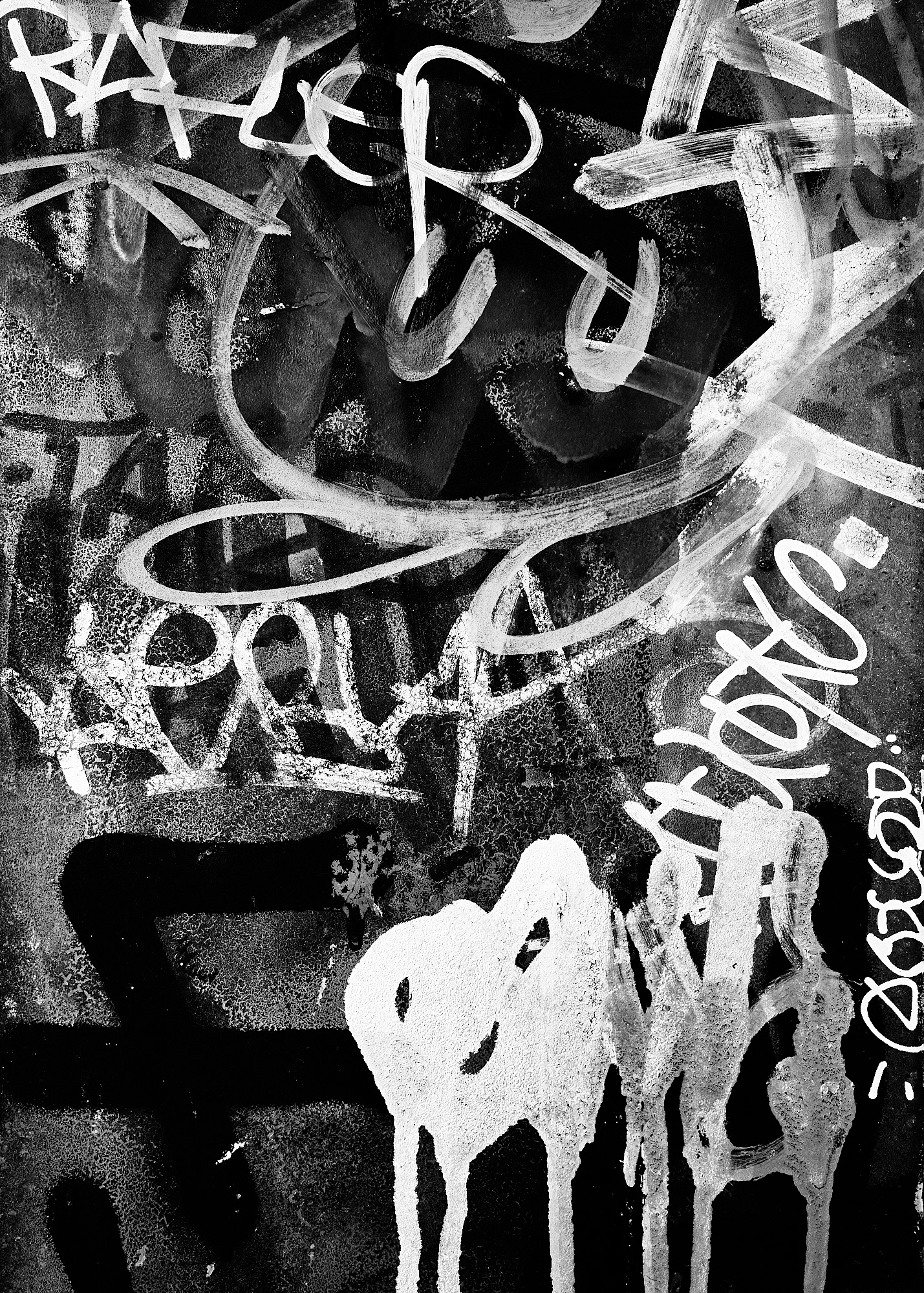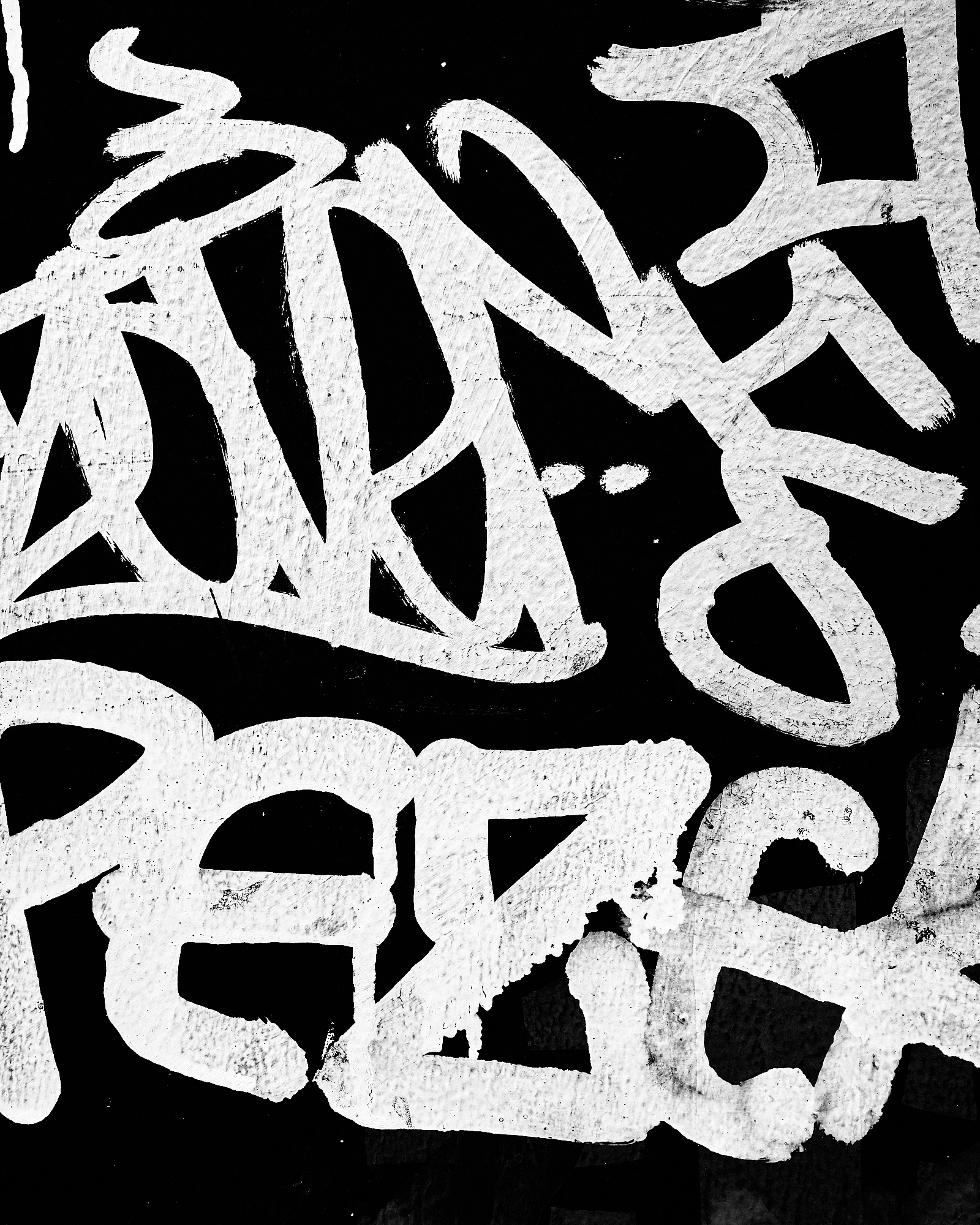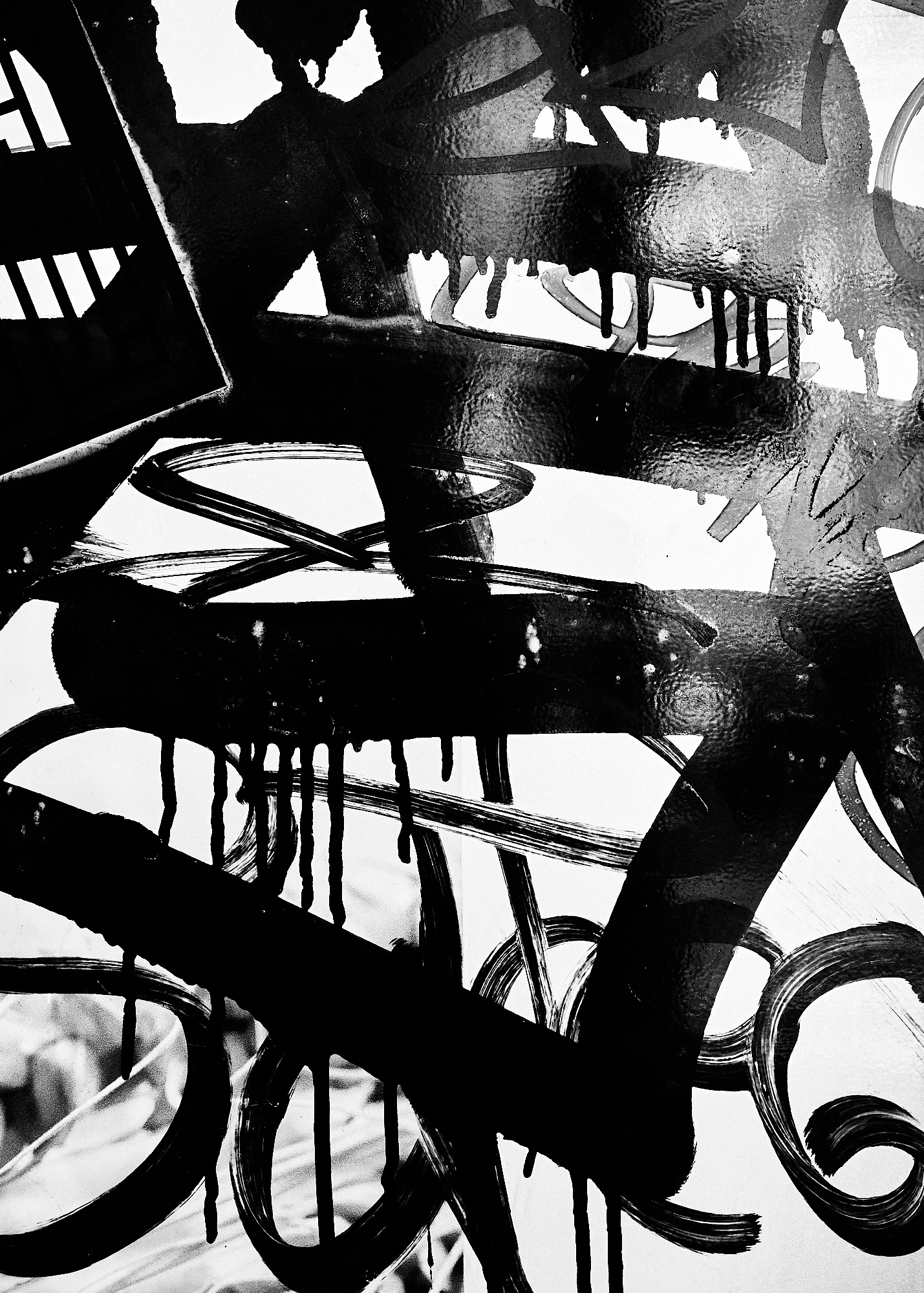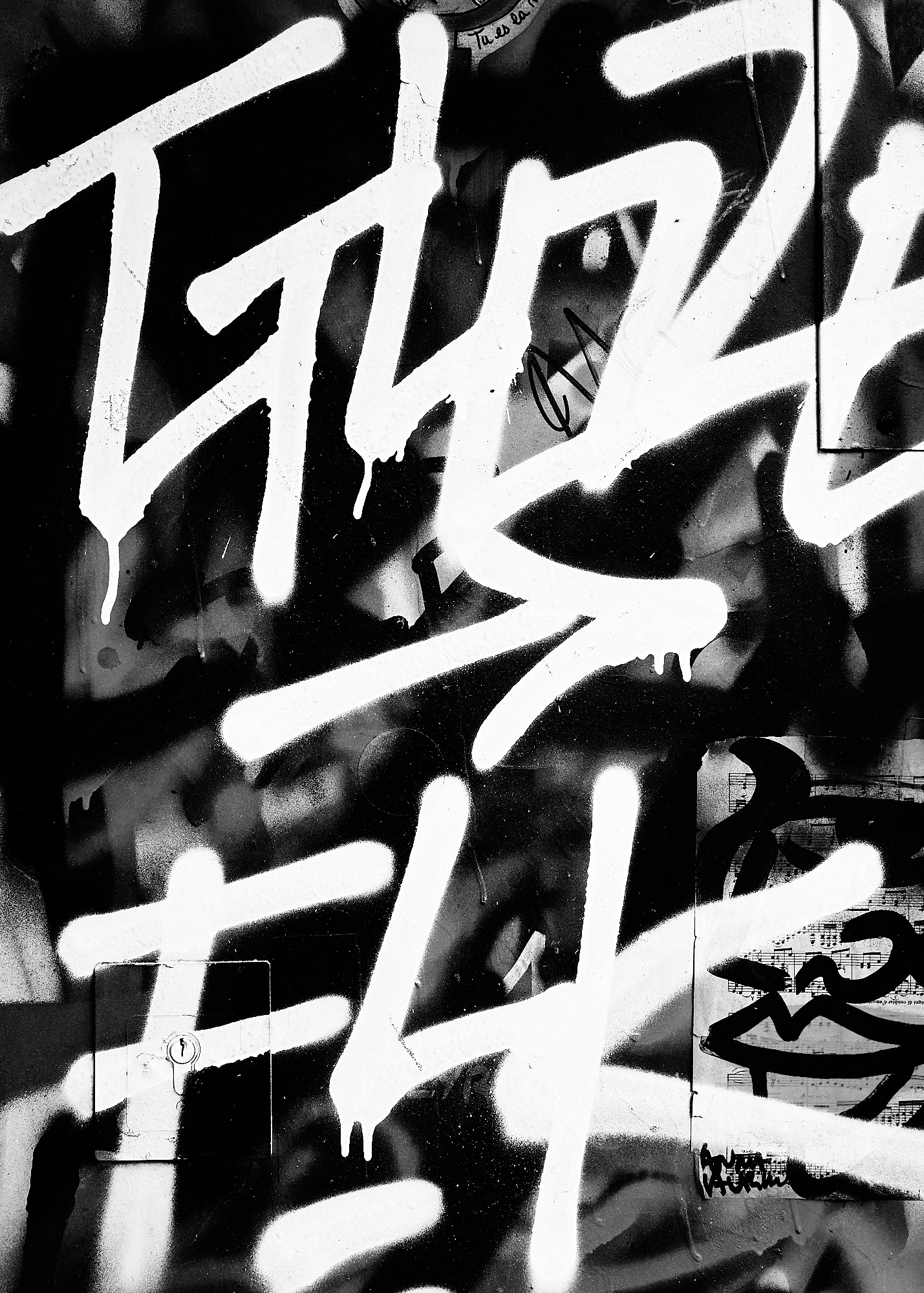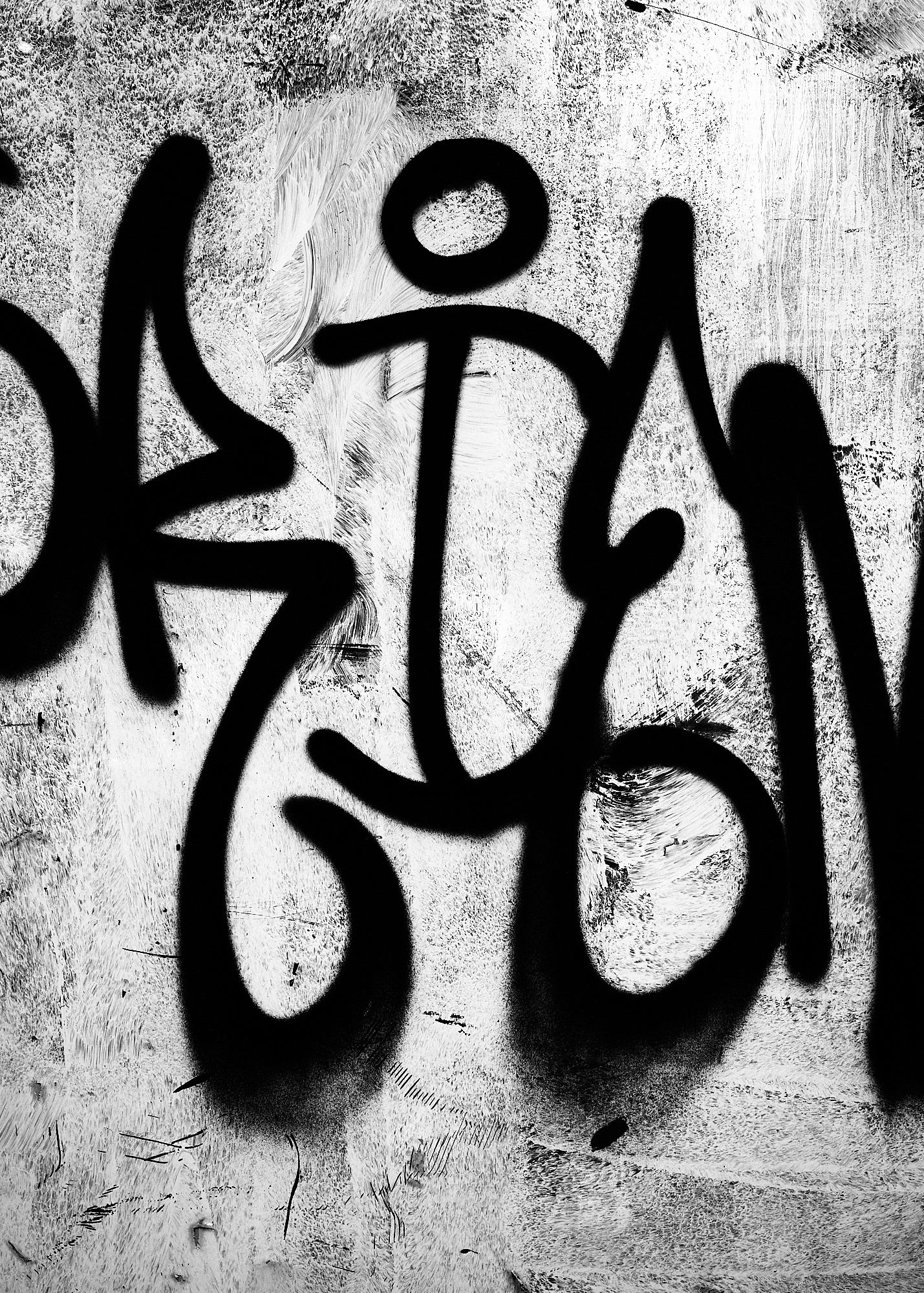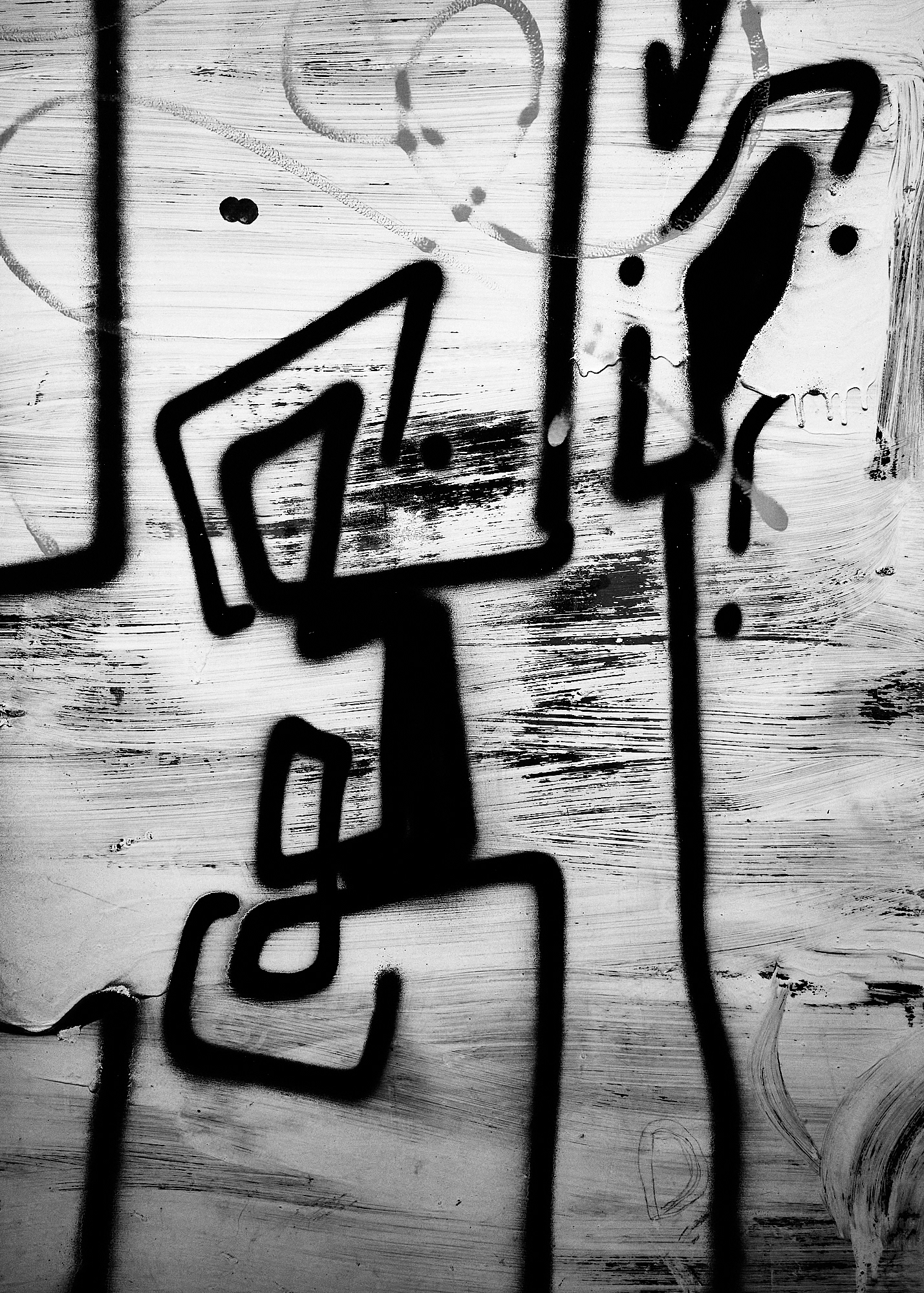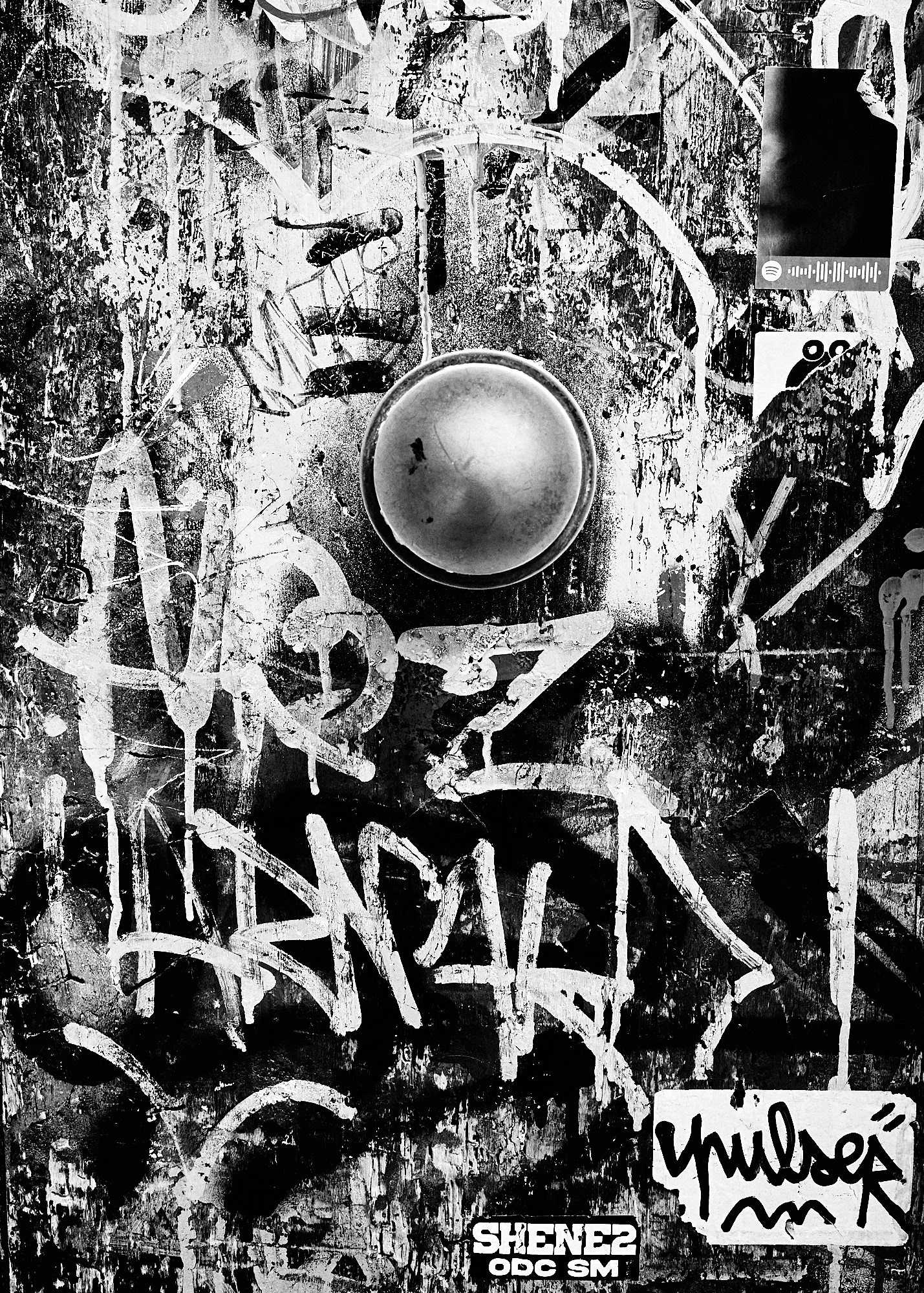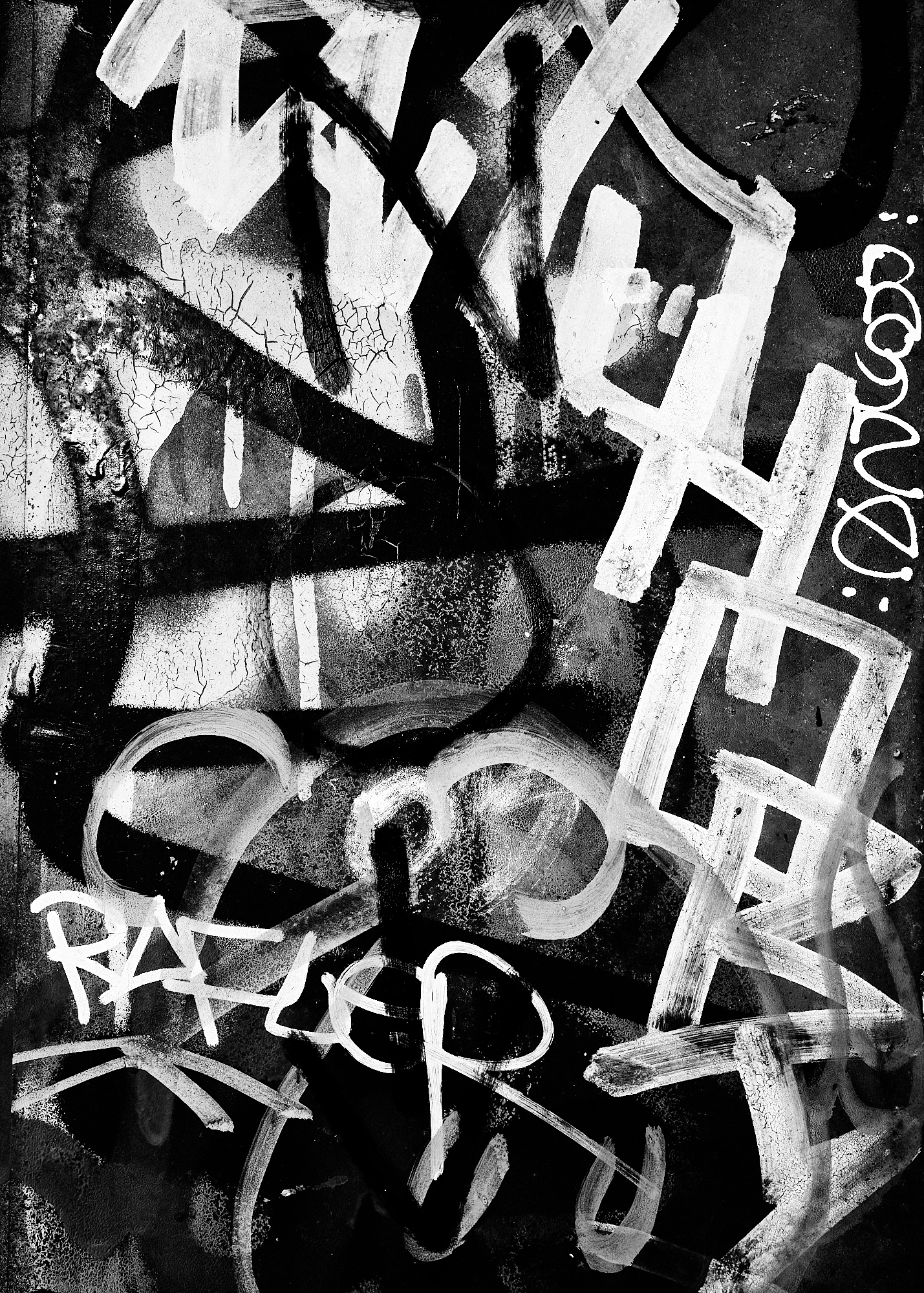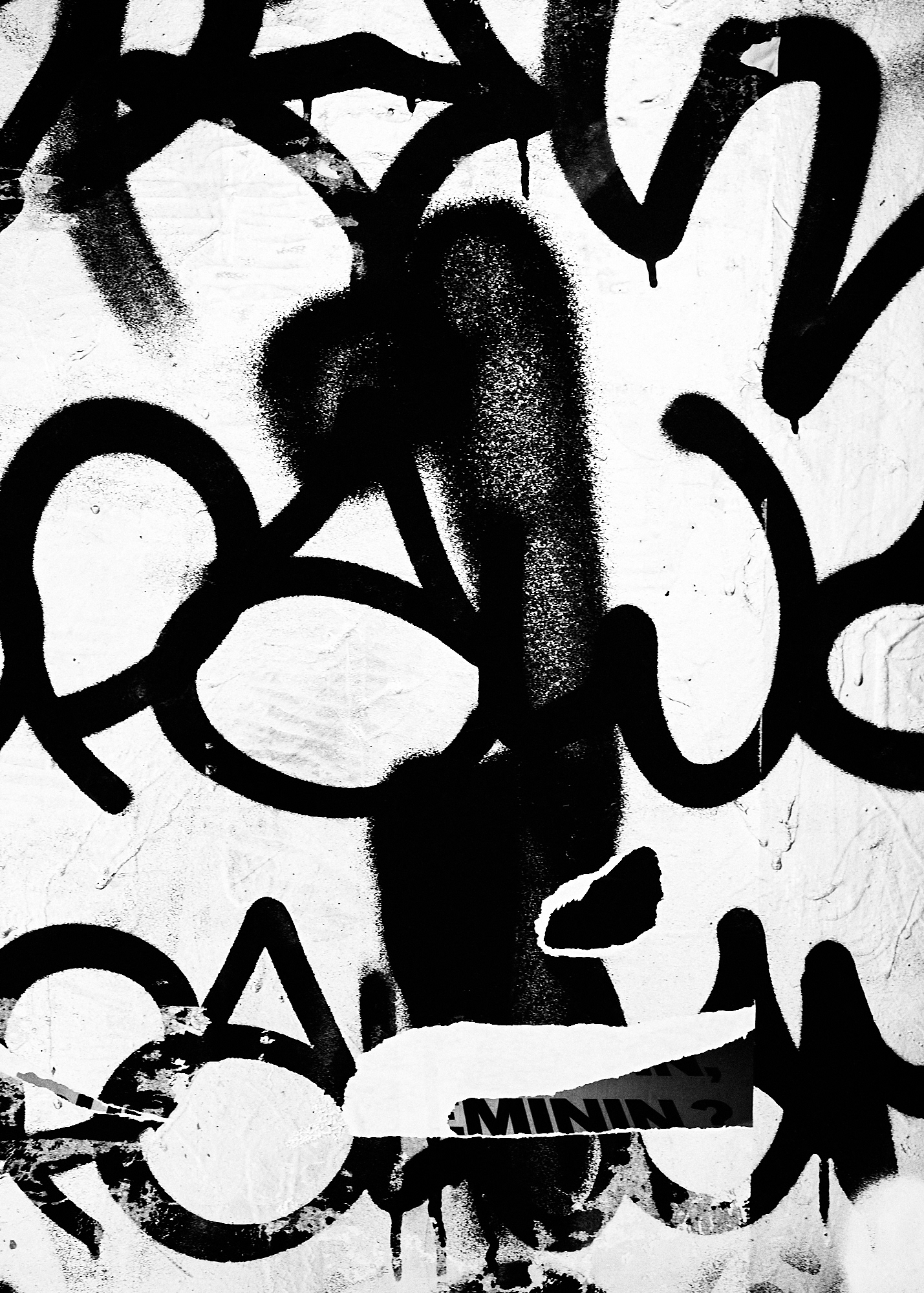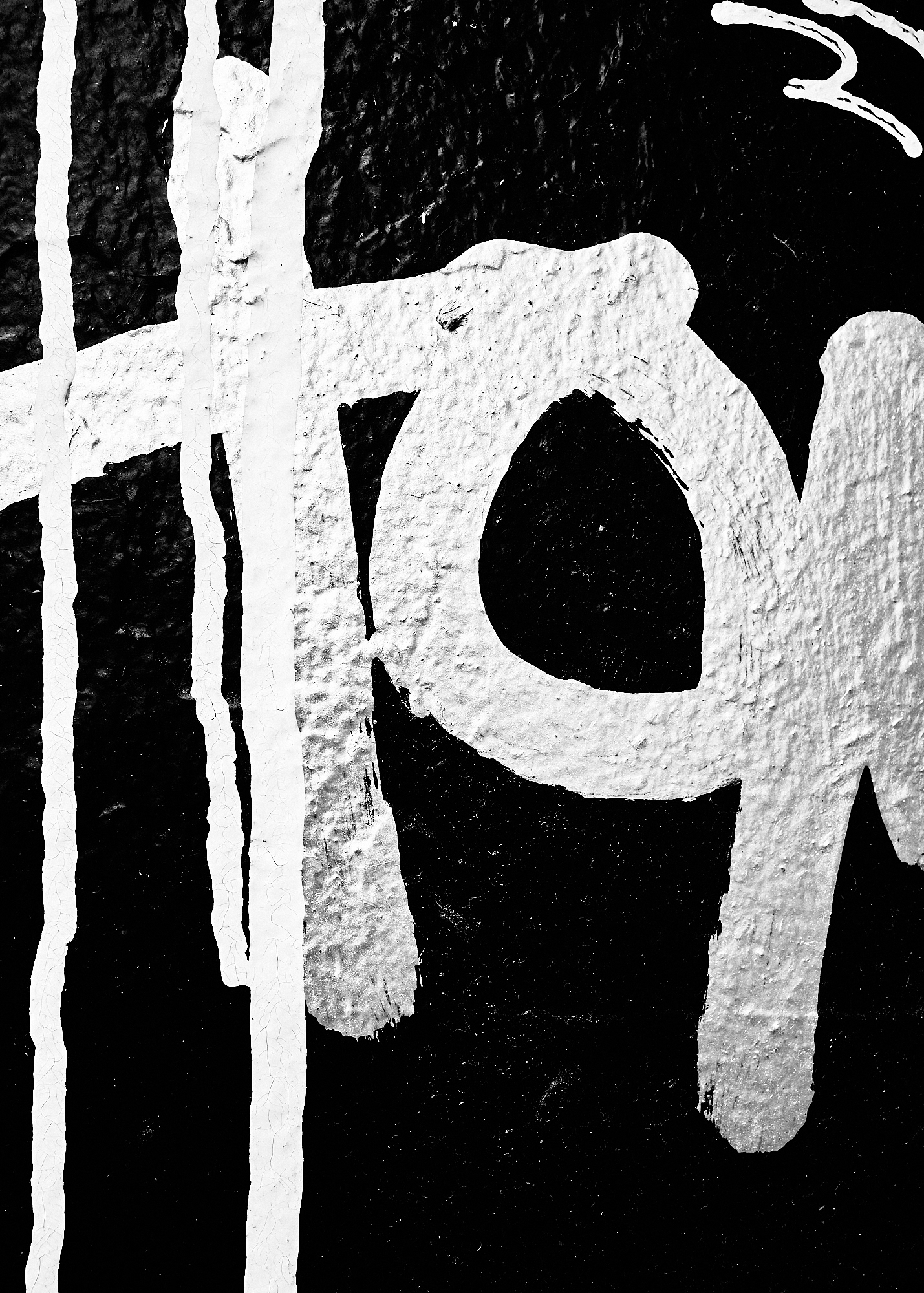
Agrégats de graffitis aux caractères entrelacés dans une densité graphique oppressante. Les lettres se mélangent sur des tons graphites et le message se perd. Le regard se trouble en cherchant le sens, l’esprit se brouille en suivant la ligne blanche.